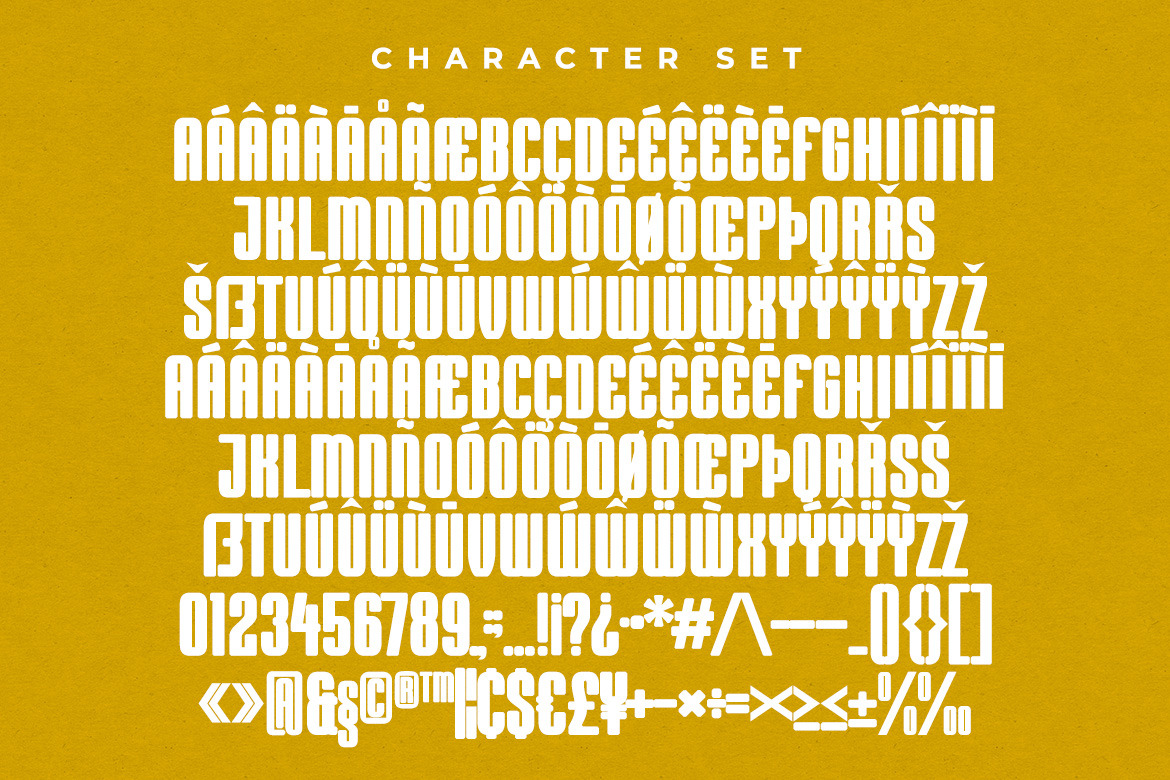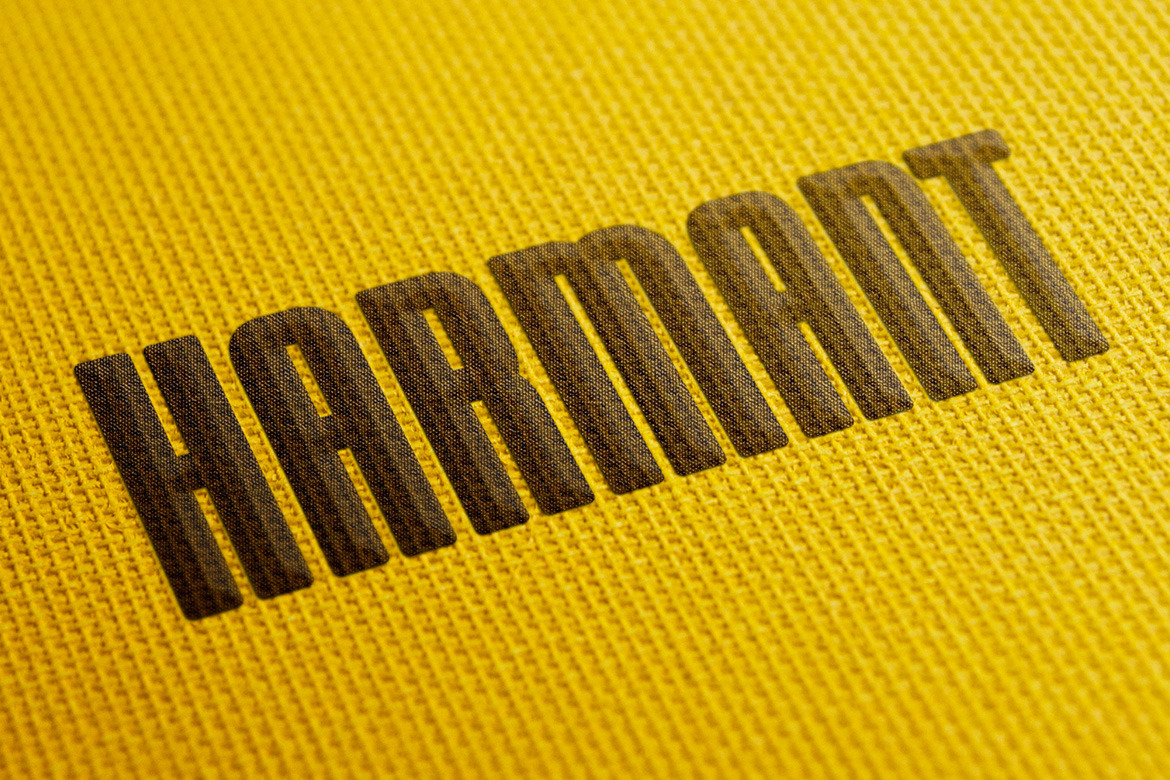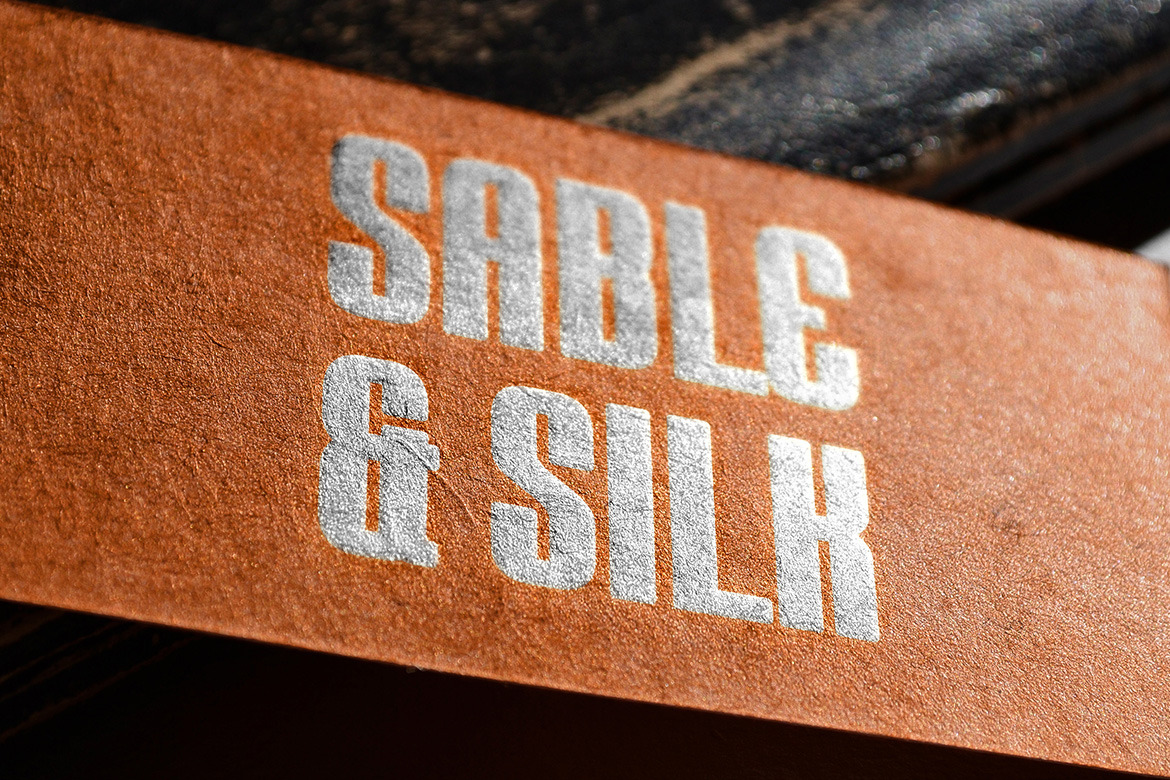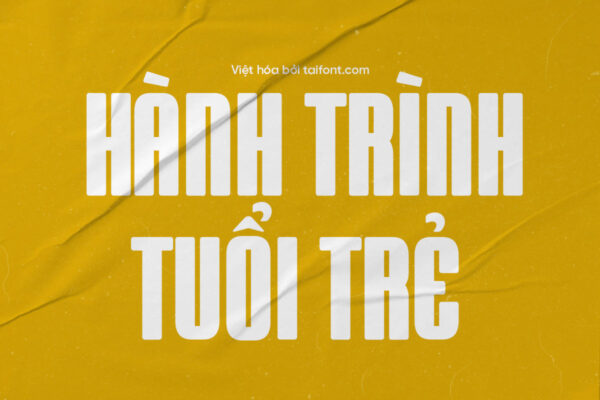
Giới thiệu về Font TF Nicha Việt hóa
TF Nicha Việt hóa là một font chữ nổi bật với thiết kế cao, to, tròn trịa và đầy đặn, mang đến vẻ ngoài dễ thương nhưng vẫn toát lên sự chắc chắn và vững chãi. Font này kết hợp giữa sự thân thiện của các nét bo tròn với chiều cao ấn tượng, tạo nên một phong cách độc đáo, thu hút ánh nhìn và dễ dàng truyền tải thông điệp một cách rõ ràng.
Với đặc điểm hình dáng độc đáo nhưng vẫn rất dễ thương, Nicha là lựa chọn lý tưởng cho các thiết kế muốn truyền tải sự vui tươi, đáng yêu và sự gần gũi nhưng vẫn đảm bảo tính vững chắc:
- Thiết kế cho trẻ em và giáo dục: Hoàn hảo cho sách truyện thiếu nhi, đồ dùng học tập, bảng hiệu trường mầm non, hoặc các ấn phẩm giáo dục. Font này giúp tạo không khí vui nhộn, ngộ nghĩnh và thân thiện với trẻ nhỏ, đồng thời các chữ cái to rõ ràng giúp các bé dễ đọc và nhận diện.
- Thiết kế bao bì sản phẩm: Lý tưởng cho bao bì các sản phẩm thực phẩm, đồ uống, hoặc đồ dùng gia đình cần sự thân thiện, an toàn và dễ nhận biết. Nét chữ to tròn giúp thông tin sản phẩm nổi bật trên kệ hàng.
- Thiết kế thương hiệu thân thiện: Phù hợp cho các thương hiệu muốn truyền tải sự trẻ trung, lạc quan, đáng tin cậy và có tính chất “healthy & safe”.
- Tiêu đề và thông báo: Tuyệt vời cho các tiêu đề, thông báo quan trọng trên các ấn phẩm in ấn hoặc kỹ thuật số, nơi cần sự chú ý nhưng vẫn giữ được vẻ mềm mại, dễ thương.
Với TF Nicha Việt hóa, bạn có thể dễ dàng thổi hồn vui tươi, đáng yêu và sự vững chãi vào các thiết kế, tạo ra những sản phẩm không chỉ đẹp mắt mà còn đầy cảm xúc và sức hút, đồng thời truyền tải thông điệp một cách rõ ràng và đáng tin cậy.
Font Việt hóa TF Nicha